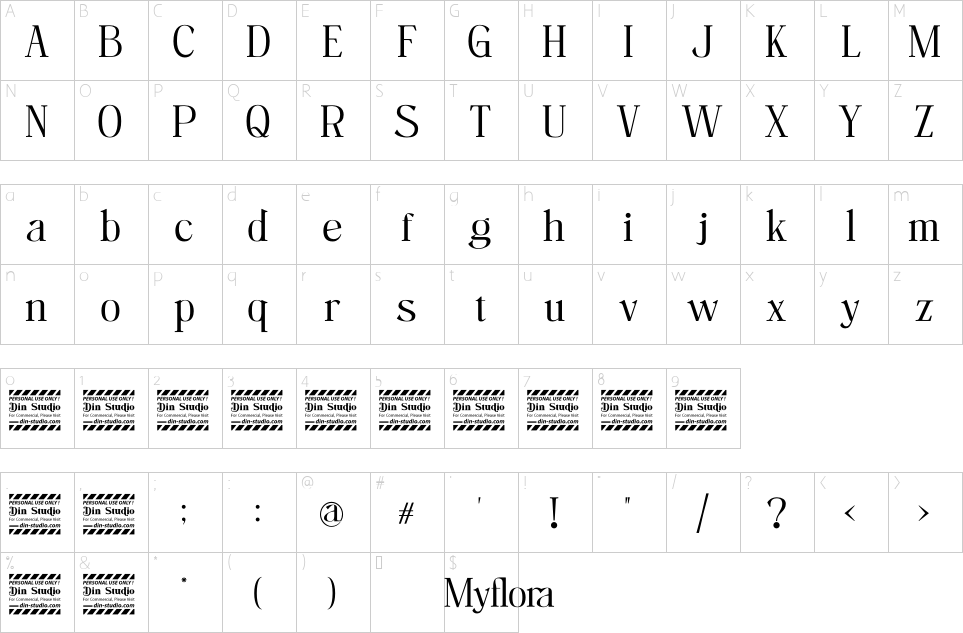
Descubra uma fonte única e elegante chamada Myflora, disponível gratuitamente tanto para Windows quanto para Mac. Desenhada pelo talentoso Natha Type, Myflora não é apenas uma fonte; é uma paixão que busca inspirar. Com uma vasta gama de caracteres, esta fonte traz uma sensação natural e envolvente, ideal para qualquer projeto que busque unir estilo com conforto. Desde textos clássicos até designs digitais, Myflora se destaca por sua capacidade de oferecer um toque autêntico e agradável a qualquer projeto. Desenvolvida para aqueles que apreciam a combinação de beleza e funcionalidade, Myflora é uma escolha inteligente para qualquer designer que busca criar um visual único e sofisticado. Com mais de mil downloads, Myflora já é uma opção confiável e de alta qualidade para qualquer projeto visual.